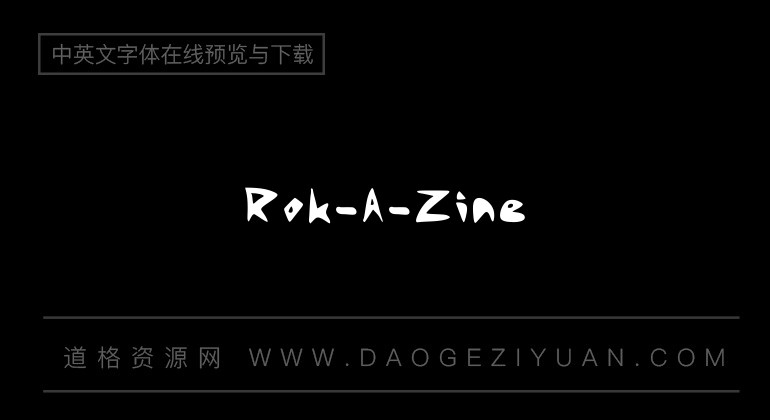
Rok-A-Zine是一种具有独特风格的数字字体,它的设计灵感源于摇滚乐的文化和视觉元素。这种字体的字形粗大而有力,字母之间的间距较小,使其具有强烈的冲击力和视觉效果。 Rok-A-Zine字体的设计师是来自美国的Tommy Larsen,他是一名资深的艺术指导和平面设计师。这种字体最初是为了一个音乐节的海报而设计的,但由于其受欢迎程度,Larsen决定将其开放给公众使用。 Rok-A-Zine字体包含了大写字母、小写字母、数字和标点符号,适用于各种不同的设计项目,如音乐海报、标志、书籍封面等。如果你正在寻找一种具有冲击力和独特风格的数字字体,Rok-A-Zine可能是一个不错的选择。内容介绍
Rok-A-Zine是一款非常不错的手写艺术字体,具有很好的视觉感,适合于文化类的宣传设计、商业类品牌的广告和产品包装设计以及个性化文字排版等较多场景。